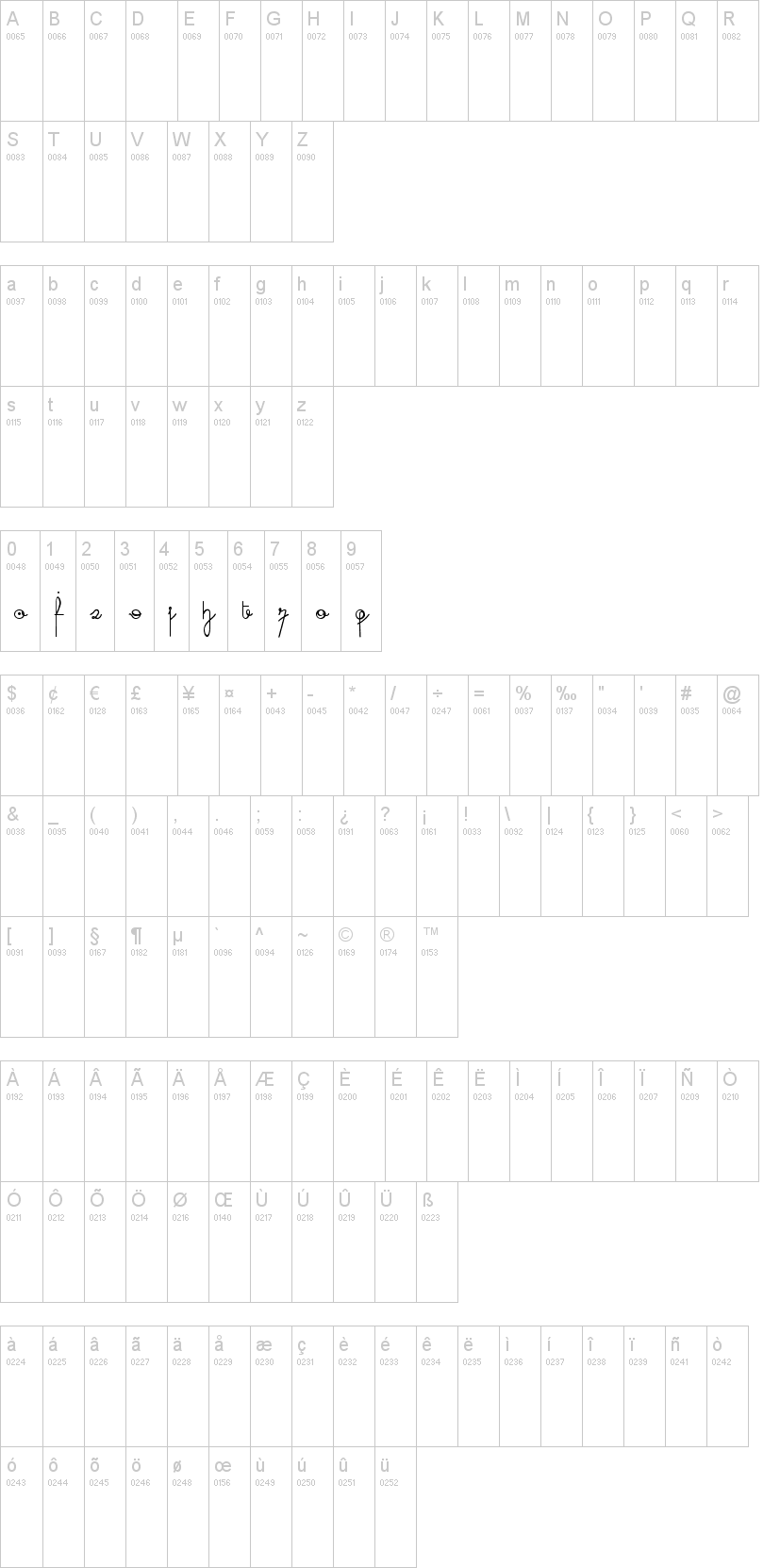
Cursive Digits 字体是一款专为数字设计的手写字体,它拥有精致的曲线和流畅的笔画,拥有自然的手写外观,可以为您的文档增添一份温暖的气息。它具有良好的可读性,可以用于各种文档,如报纸、杂志、书籍、广告等等。它可以让您的文档更加生动,使您的文字更具有魅力。内容介绍
Cursive Digits是一款非常不错的手写艺术字体,具有很好的视觉感,适合于文化类的宣传设计、商业类品牌的广告和产品包装设计以及个性化文字排版等较多场景。